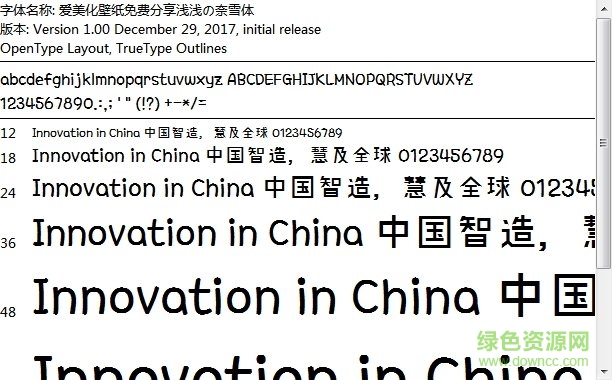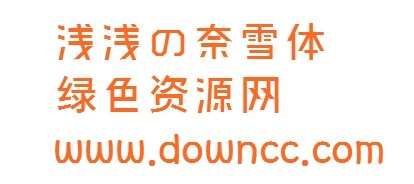
奈雪體是淺淺自制字體, 有愛美化壁紙免費分享,字跡清晰端正,有著較好的幾何圖案的筆畫,英文字體和數(shù)字字體更顯圓潤活潑,獨具美感,更多特色請來綠色資源網(wǎng)體驗吧!
淺淺奈雪體支持中英文和繁簡體輸入,并無多余的裝飾和點綴圖案,讓文字更加質樸美觀,英文十分活潑,中文較為嚴肅,各有特色,所以有著比較廣泛的使用范圍。